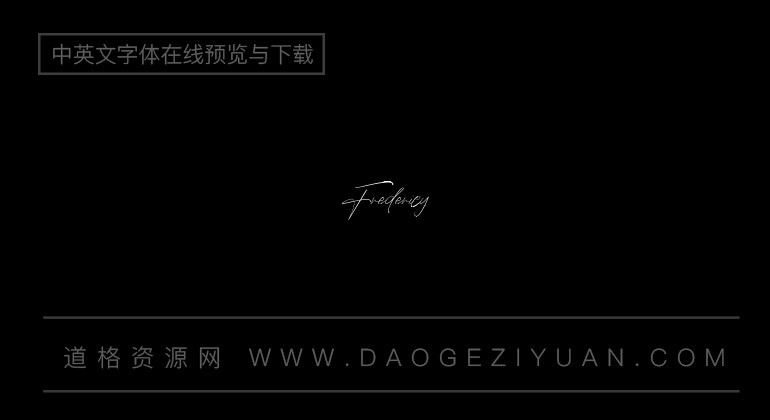
Fredericy
Fredericy字体是一款由英国设计师Paula Nazal Selaive创作的英文字体,它具有现代感,可以用于印刷和网络设计中。它的外观与传统的罗马字体有所不同,具有非常优美的线条,可以增强文字的可读性,同时又不失其美感。它的字符结构更加简洁,使用起来更加方便,可以为设计师提供更多的灵活性和创意空间。
Fredericy是一款非常不错的手写艺术字体,具有很好的视觉感,适合于文化类的宣传设计、商业类品牌的广告和产品包装设计以及个性化文字排版等较多场景。